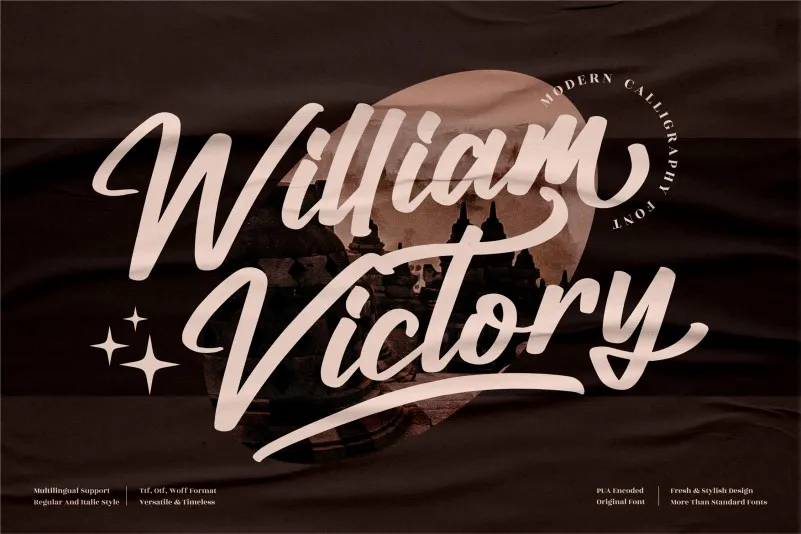
A William Victory Font é uma elegante opção para designers em busca de adicionar um toque sofisticado a seus projetos digitais ou impressos. Este script premium é perfeito para qualquer projeto que exige um grau elevado de sofisticação, seja criação de logotipos e campanhas de marca, até mesmo personalização de embalagens de produtos ou arte para livros. A fonte oferece uma versatilidade impressionante, ideal para aplicar em designs variados como mugs, cartões de convite, materiais de viagem, selos, ilustrações digitais e até mesmo em design fotográfico. Seja qual for seu projeto de alta qualidade, William Victory Font está aqui para garantir um brilho único e profissional.